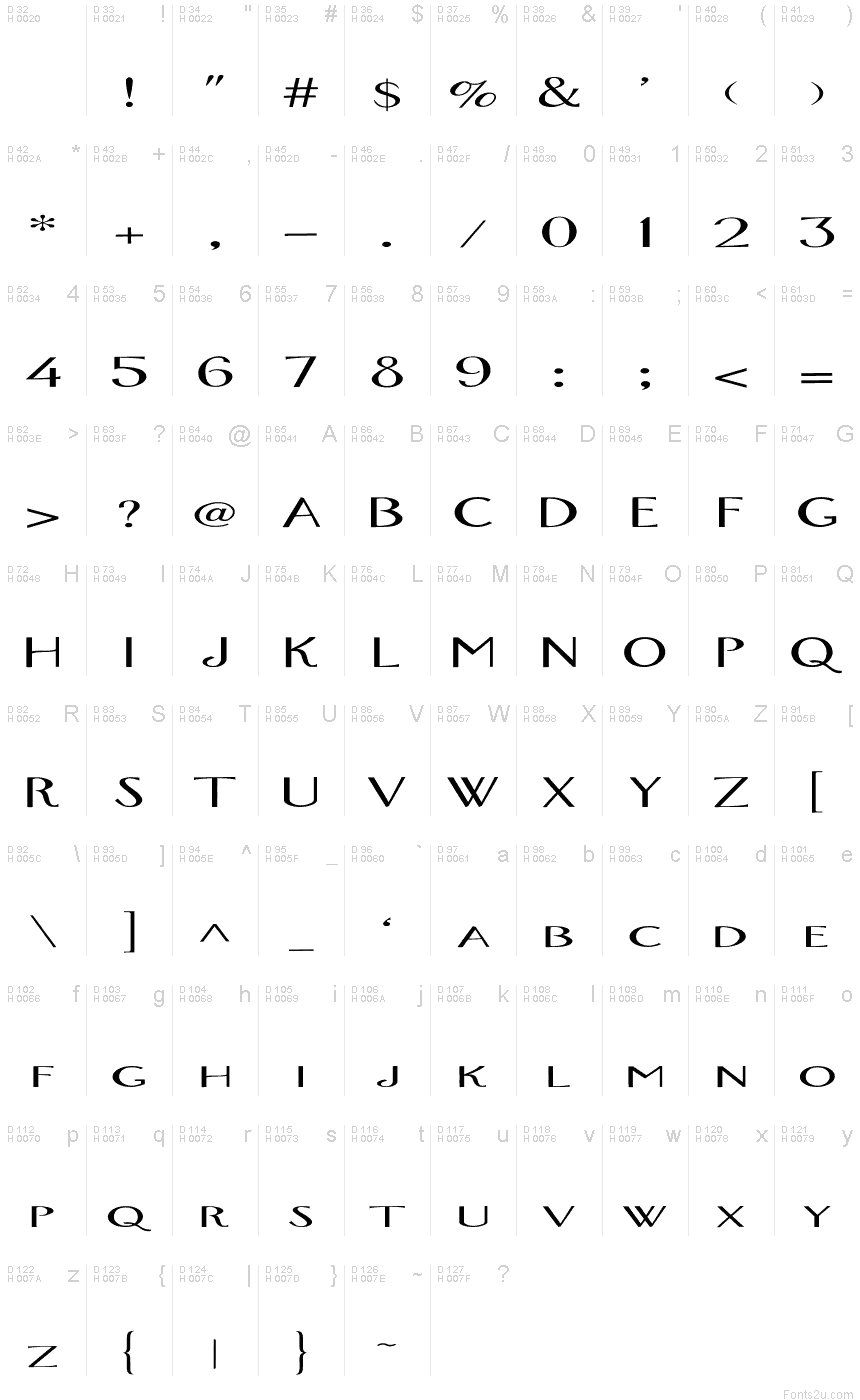
Orlando Bold ist eine kostenlose, kontrastreiche serifenlose Display-Schrift mit breiten, präzise konstruierten Großbuchstaben. Fließende Kurven treffen auf dünne horizontale Striche, und die kantigen Buchstaben besitzen ein schlichtes, architektonisches Finish.
Mode- und Luxusthemen passen zu ihren dramatischen Proportionen, wodurch sie sich für Magazincover, Parfümverpackungen und Eventplakate eignet. Der wiederkehrende Mix aus weiten Schwüngen, spitzen Winkeln und schlanken Querabstrichen kann im Editorial Design geometrische Fotografie oder stromlinienförmige Produktbilder widerspiegeln.